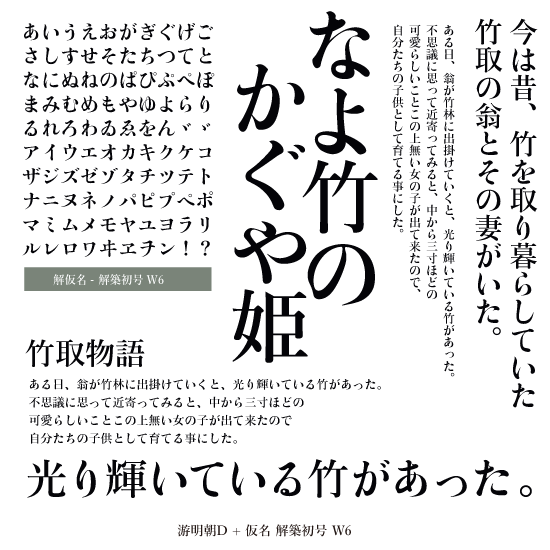
解仮名- 解築初号 W6
◉築地活版製造所の号数活字の中で一番大きな見出し用活字が初号でした。築地初号はたっぷりとした肉付けで見事な揺るぎようのない絶妙なフォルムを形成しています。民友社の国民新聞に供給され民友仮名とも云われました。時代を越えて営々と息づくなかで「と」「そ」「お」「え」「し」などは世々の仮名使用の変遷に伴い都度アレンジされています。「解築初号」は電子組版用に現代の標準的な字形を採って翻刻しました。